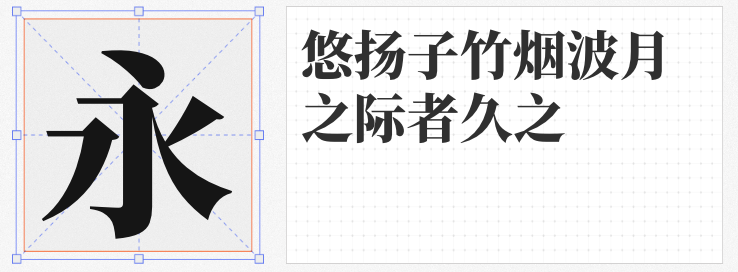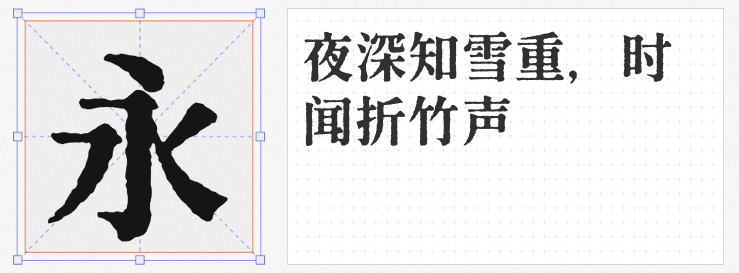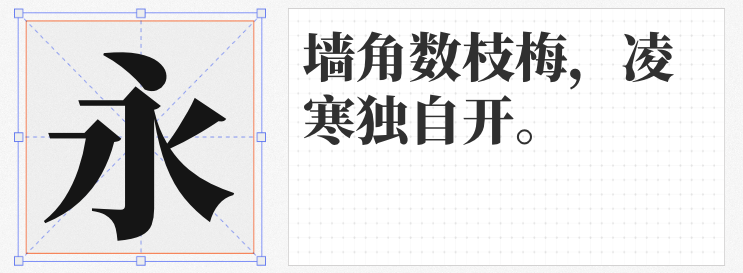
在设计中,宋体因其独特的文化底蕴与视觉表现力,始终是标题、正文及品牌视觉的经典选择。本文推荐四款免费可商用的宋体字体,涵盖现代简约、柔和雅致、复古斑驳等风格,满足多元设计需求。
由Adobe与Google联合开发的思源宋体 CN Heavy,是思源黑体的“宋体兄弟”,支持简体中文、繁体中文、日语、朝鲜语及拉丁语系,覆盖全球超7亿用户。其 Heavy 字重笔画粗壮有力,适合作为标题或强调文字,在海报、LOGO设计中展现沉稳大气的视觉效果。作为开源字体,可放心用于商业项目。
香萃潮汐宋 W40以圆角设计打破传统宋体的棱角感,笔画间自然粘连,形成如潮汐般的流动质感。横细竖粗的强烈对比,搭配光滑曲线,既保留宋体的古典雅韵,又赋予现代设计的清新感。适用于书刊封面、广告标题或包装设计,甚至能通过“藕断丝连”的笔画营造恐怖题材的朦胧张力。
昭源宋体 Heavy与昭源黑体系列同源,专为屏幕显示优化,同时兼顾印刷质感。其字重丰富、收字量大,适合需要长文本阅读的场景(如网页正文、电子书)。 Heavy 字重笔画饱满,与昭源黑体搭配使用,可轻松构建品牌视觉的层次感,是免费字体中少见的“全能型选手”。
基于日本开源字体改造的寒蝉活宋体 復 Bold,以斑驳纹理复刻古籍的岁月痕迹,适合需要怀旧氛围的设计(如电影海报、文创品牌)。其 Bold 字重强化了笔画的粗犷感,与思源宋体的现代感形成鲜明对比,为设计师提供更多风格化选择。
这四款宋体字体各具特色,从全球化设计到本土化表达,从现代简约到复古情怀,均支持免费商用。无论是品牌视觉、出版印刷还是数字媒体,都能找到适配之选,助力设计兼具美感与合法性。